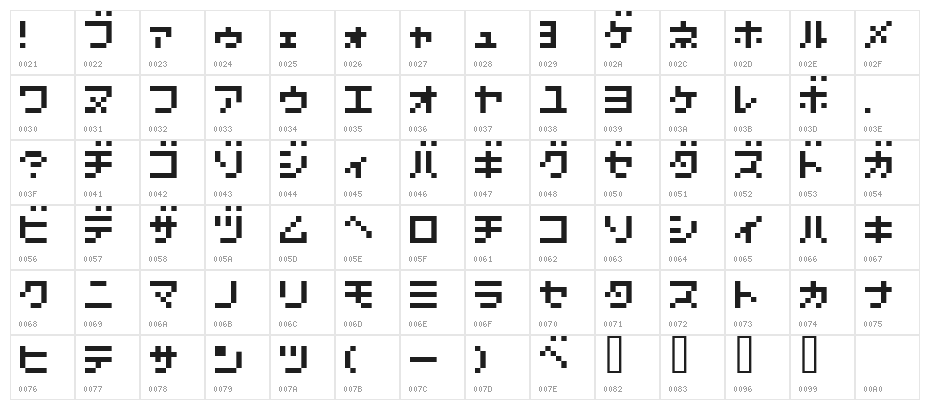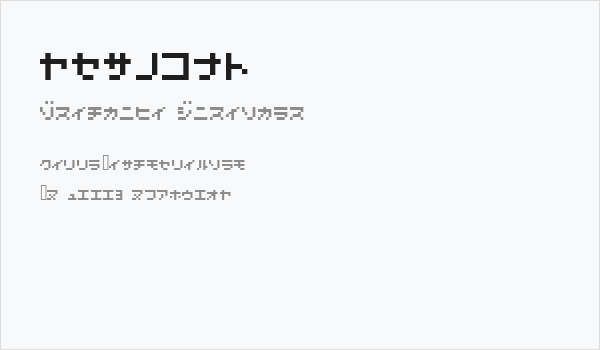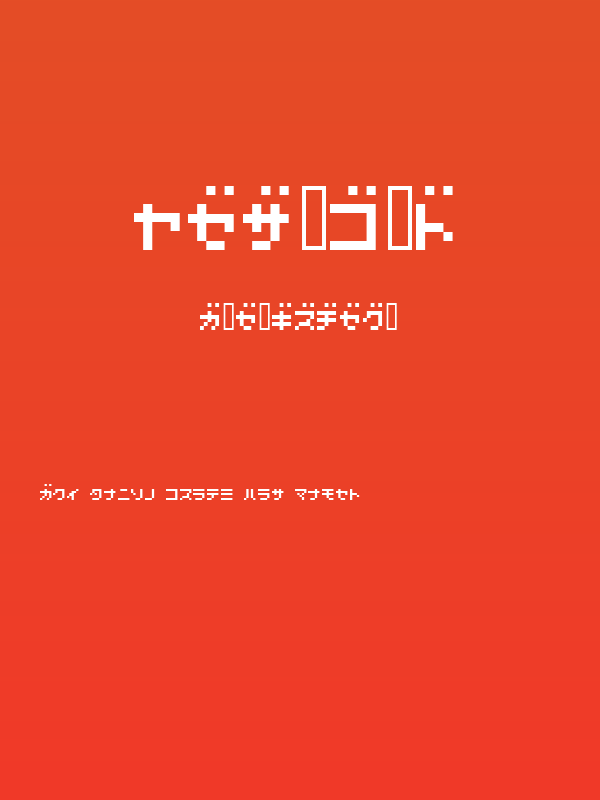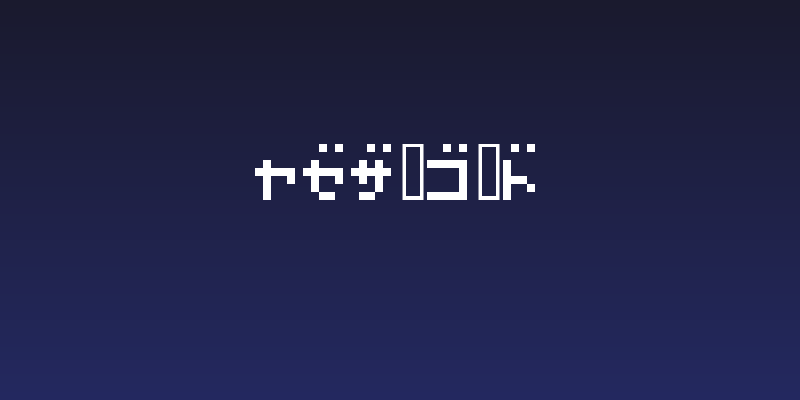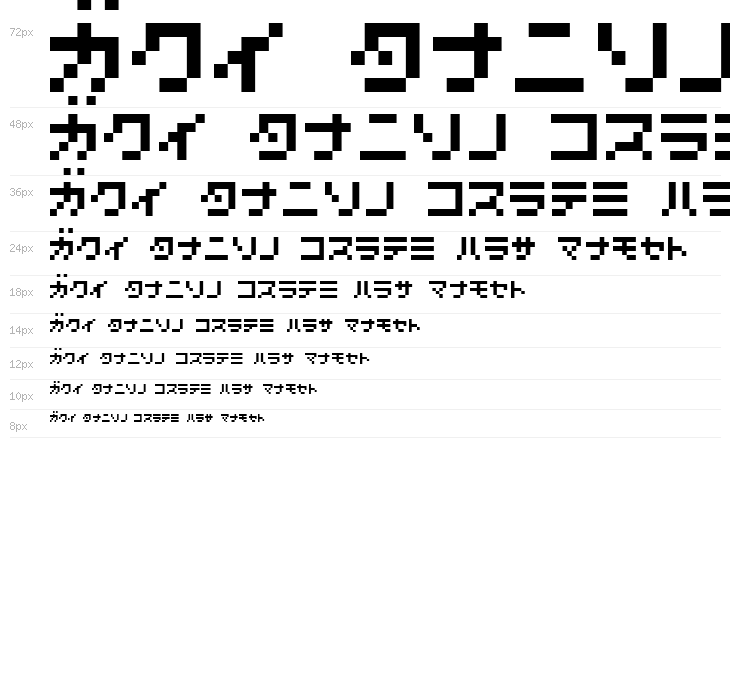
7pxkbus Font
| Progetti proposti | Ideal for retro video game designs, tech-themed posters, digital art projects, and any creative work that seeks to evoke a sense of nostalgia for early computing. |